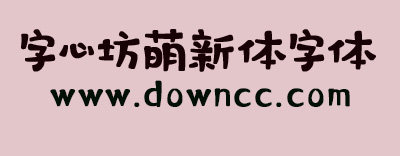
字心坊萌新體免費(fèi)字體
字心坊萌新ttf是一個(gè)免費(fèi)的藝術(shù)字體。這款字體很受萌妹子們的喜愛,外形萌萌的,在平面設(shè)計(jì)行業(yè)使用的非常廣泛。能夠在win7、win8等主流操作系統(tǒng)上安裝使用!歡迎下載體驗(yàn)。
字心坊萌新字體外形結(jié)構(gòu)圓潤可愛,字形活潑清新,具有很強(qiáng)的視覺效果,可適合應(yīng)用于藝術(shù)設(shè)計(jì)、平面宣傳設(shè)計(jì)、網(wǎng)頁設(shè)計(jì)等領(lǐng)域!喜歡的網(wǎng)友快來綠色資源網(wǎng)下載吧!